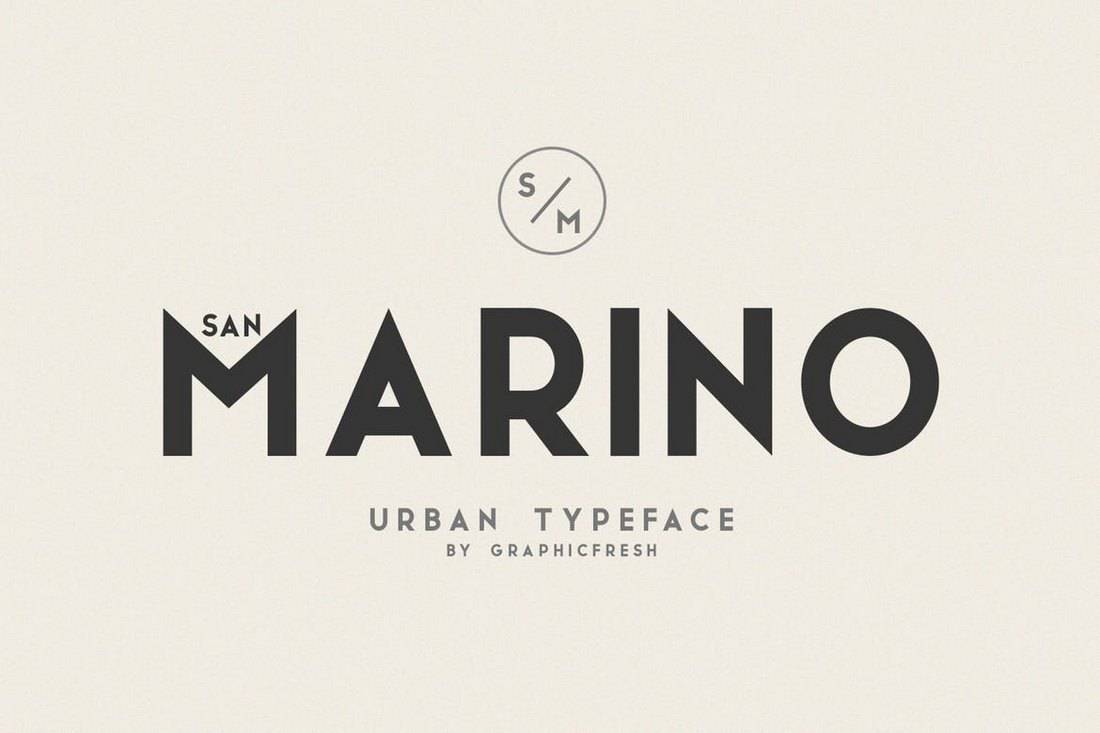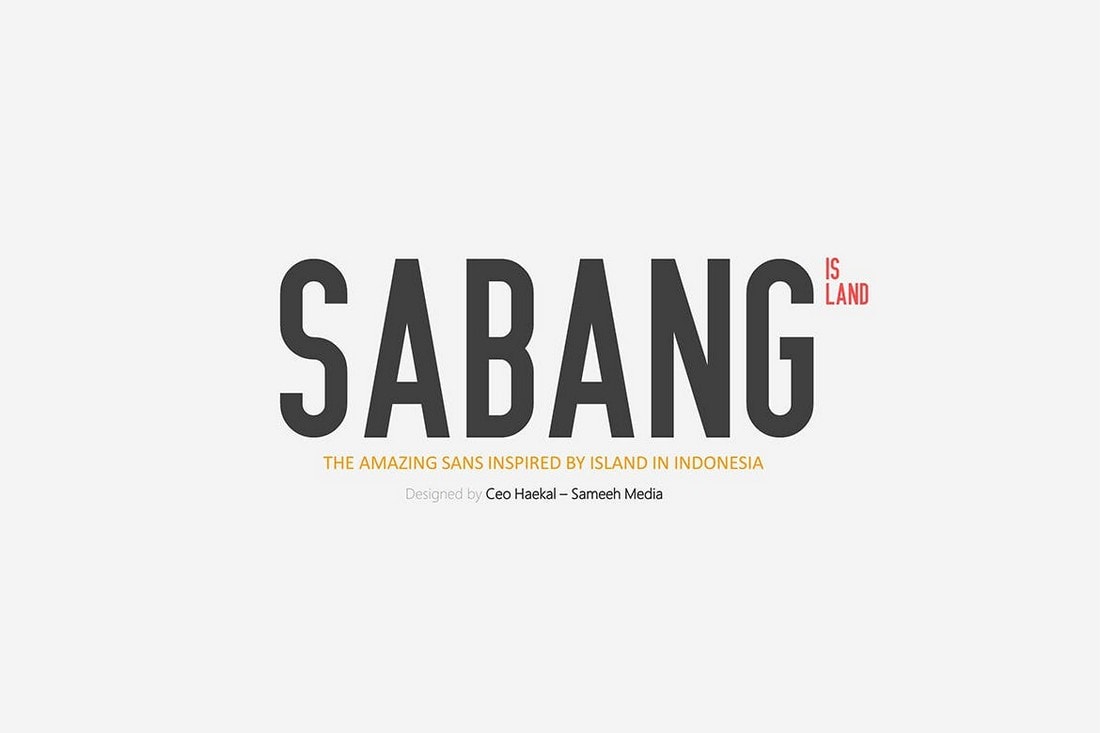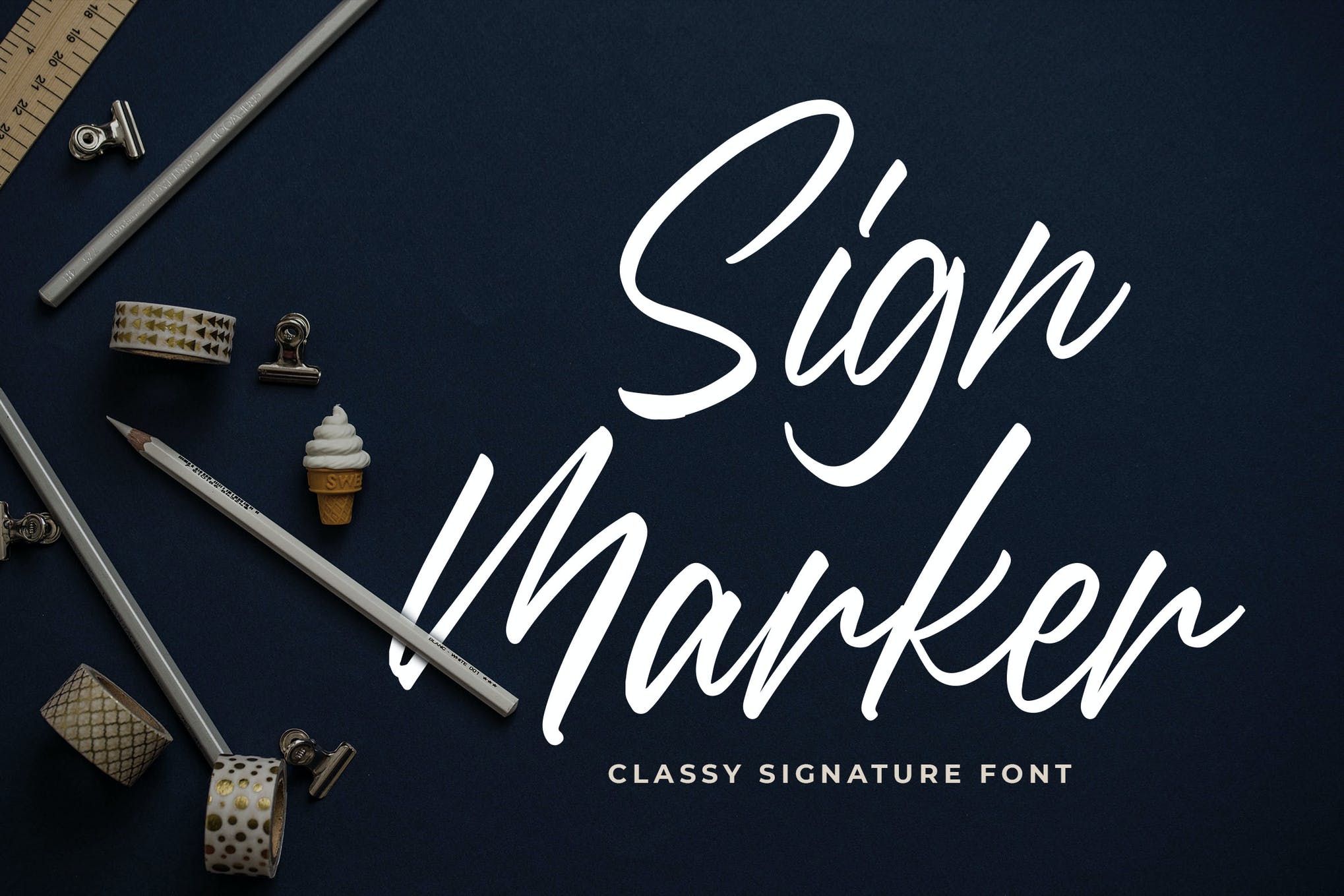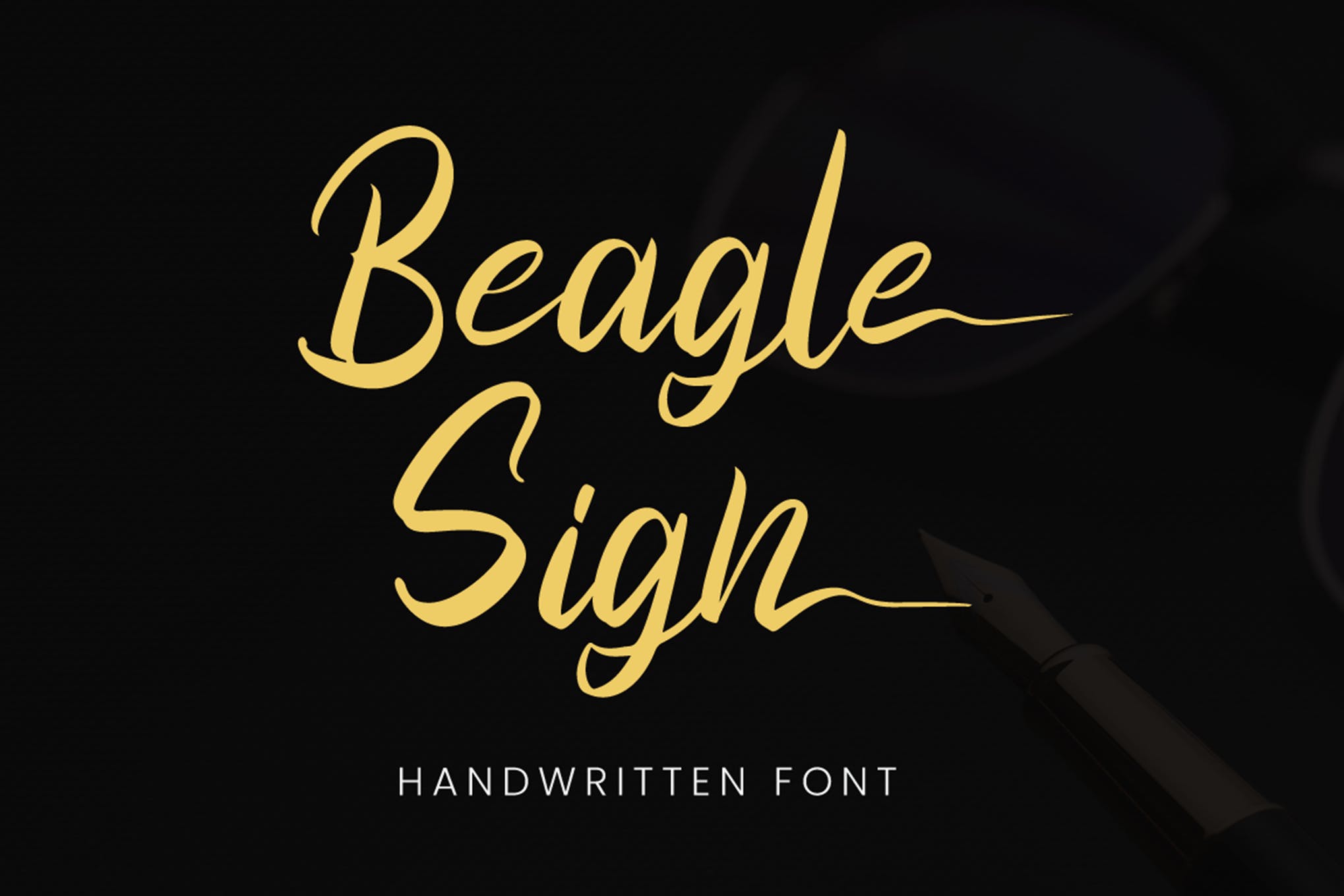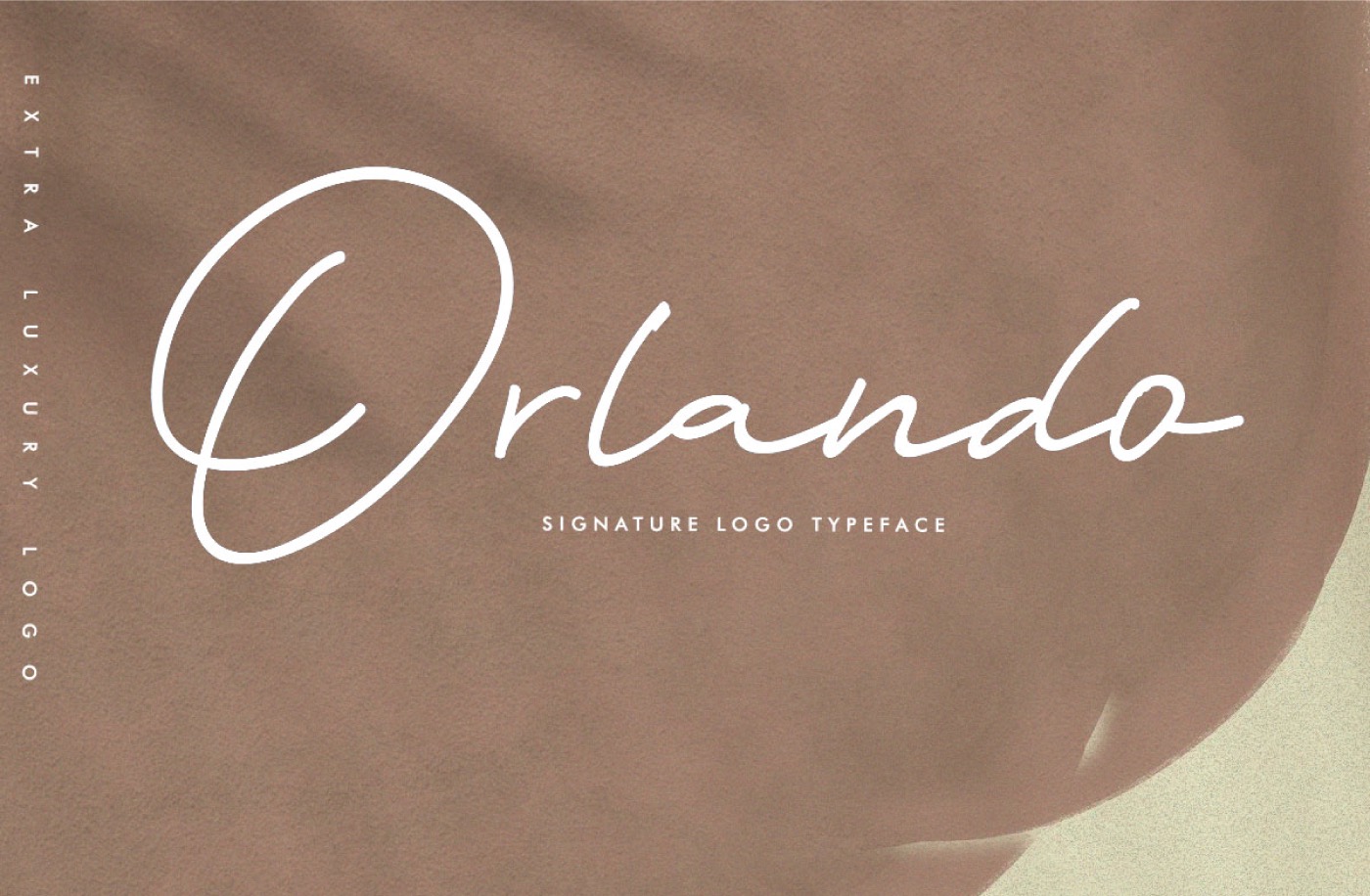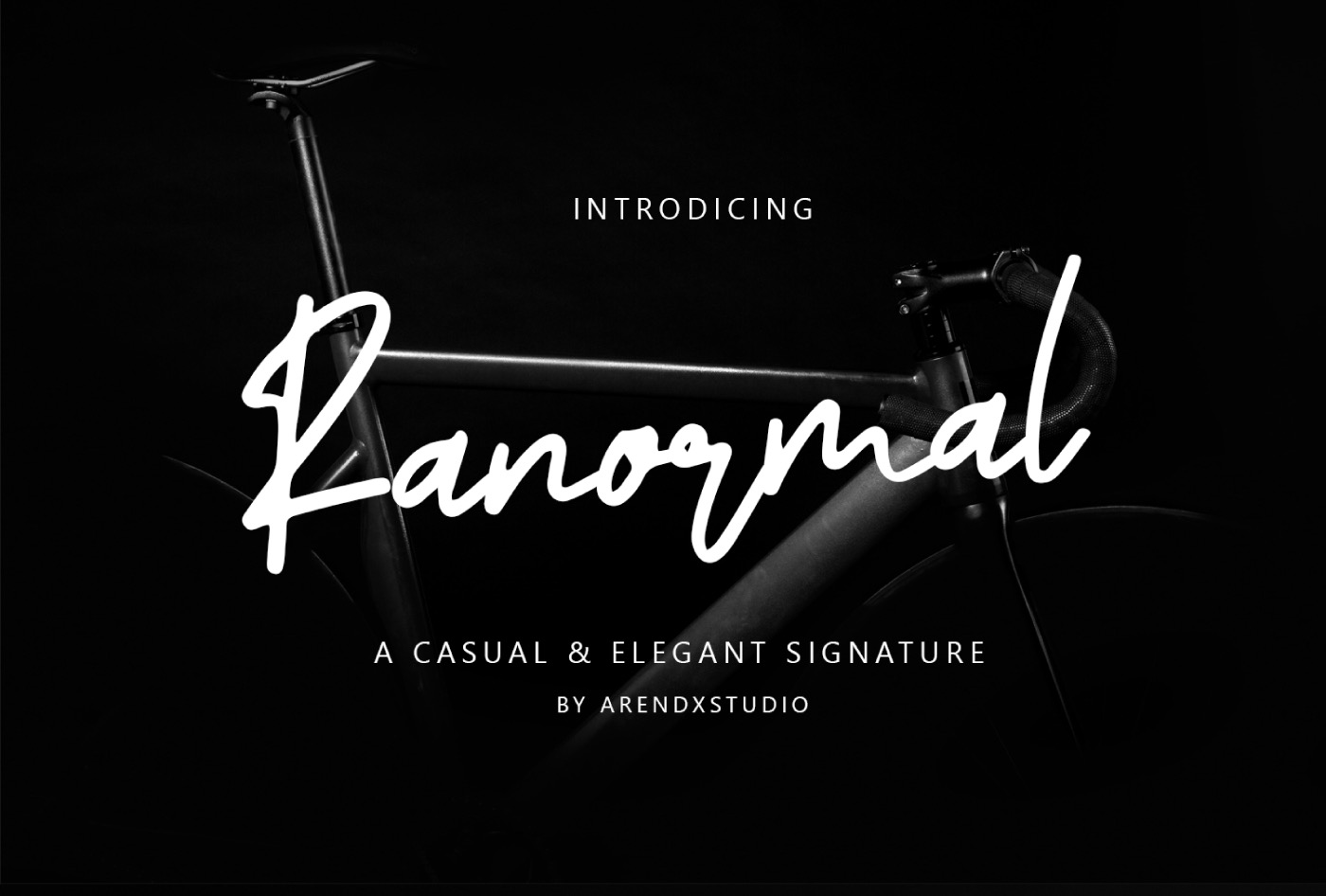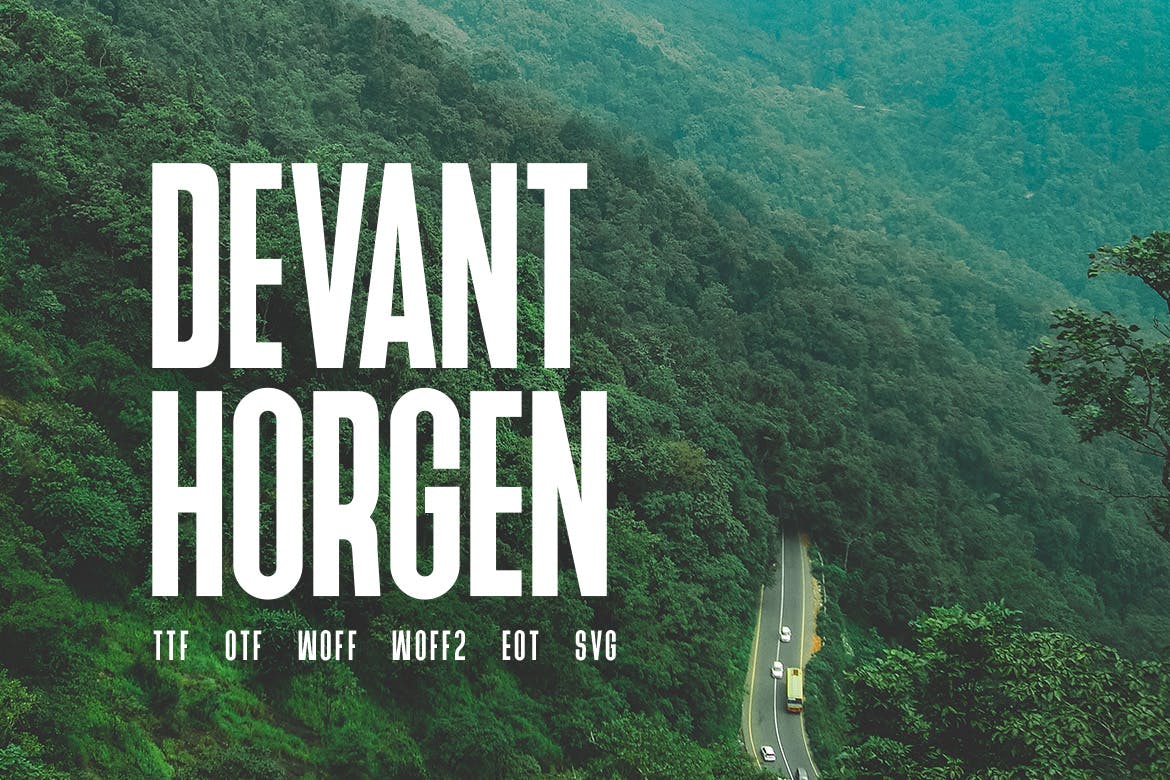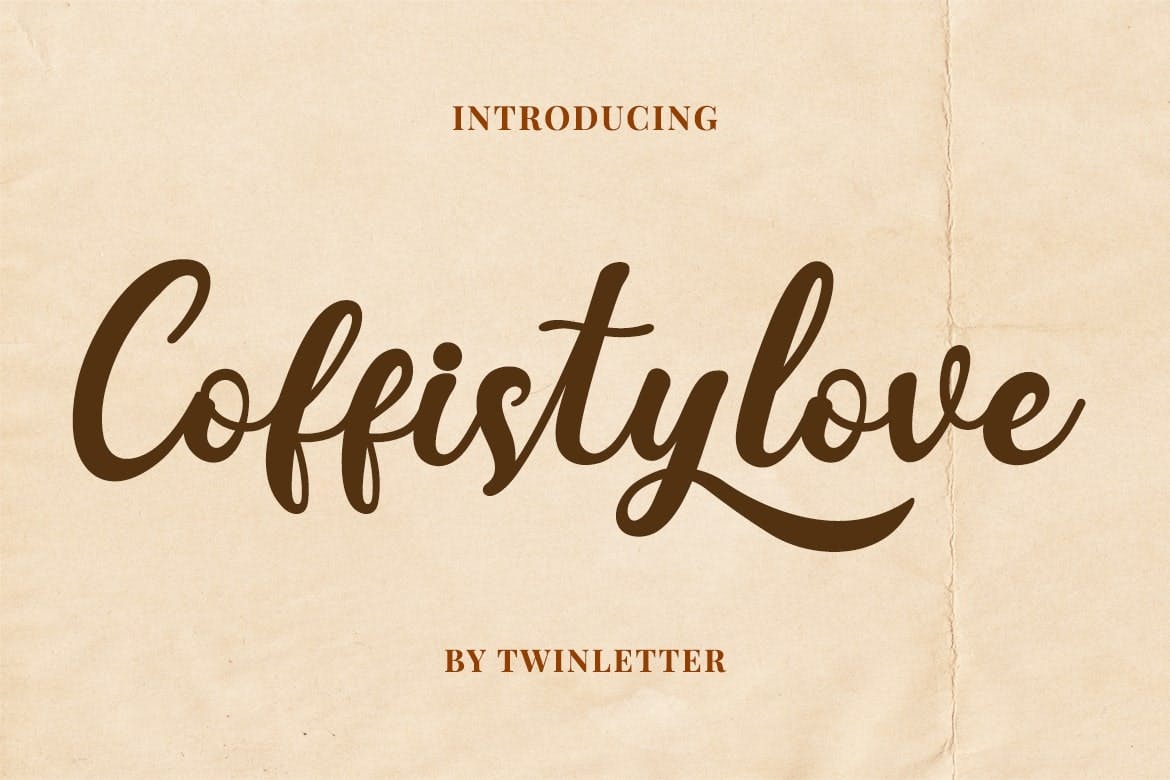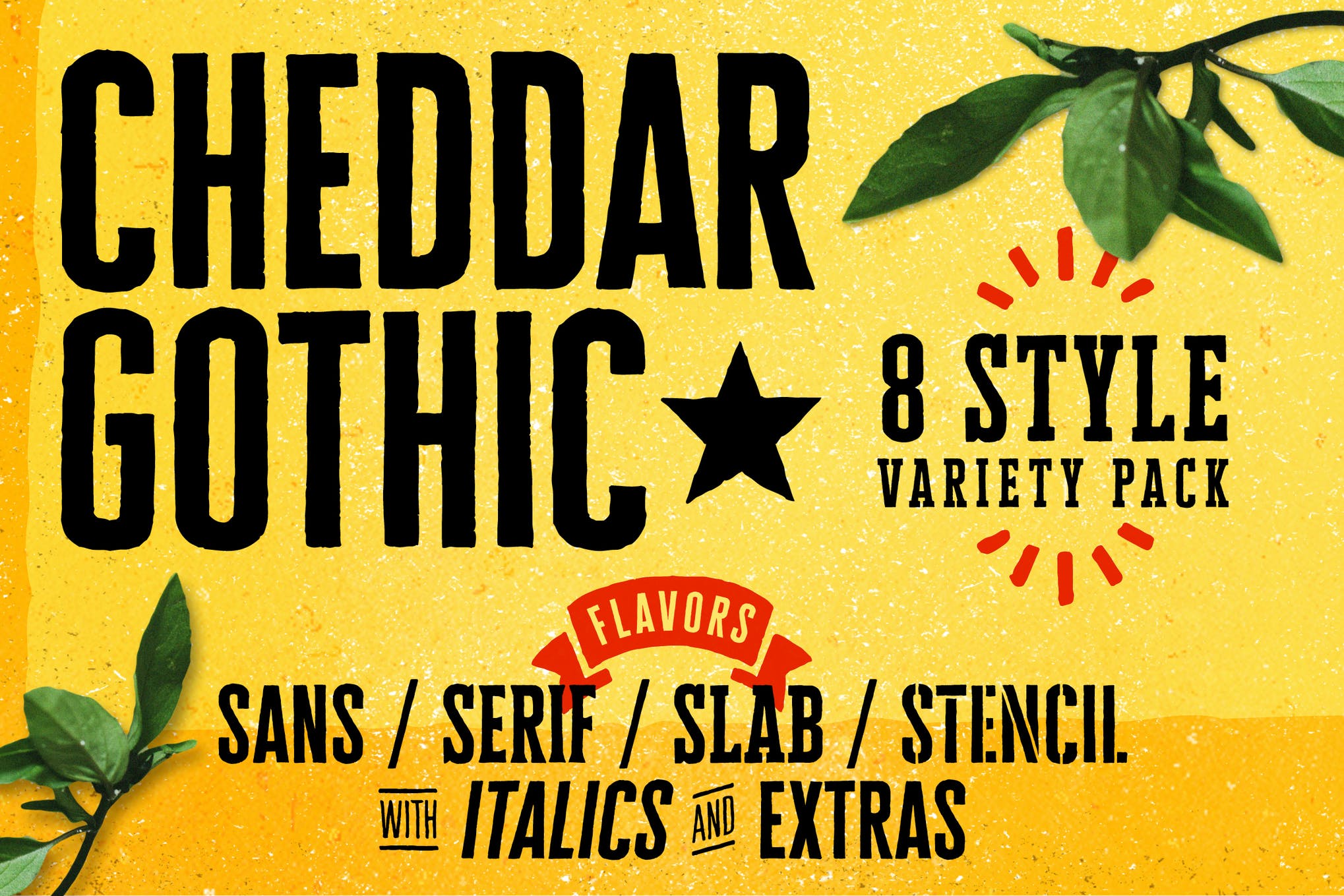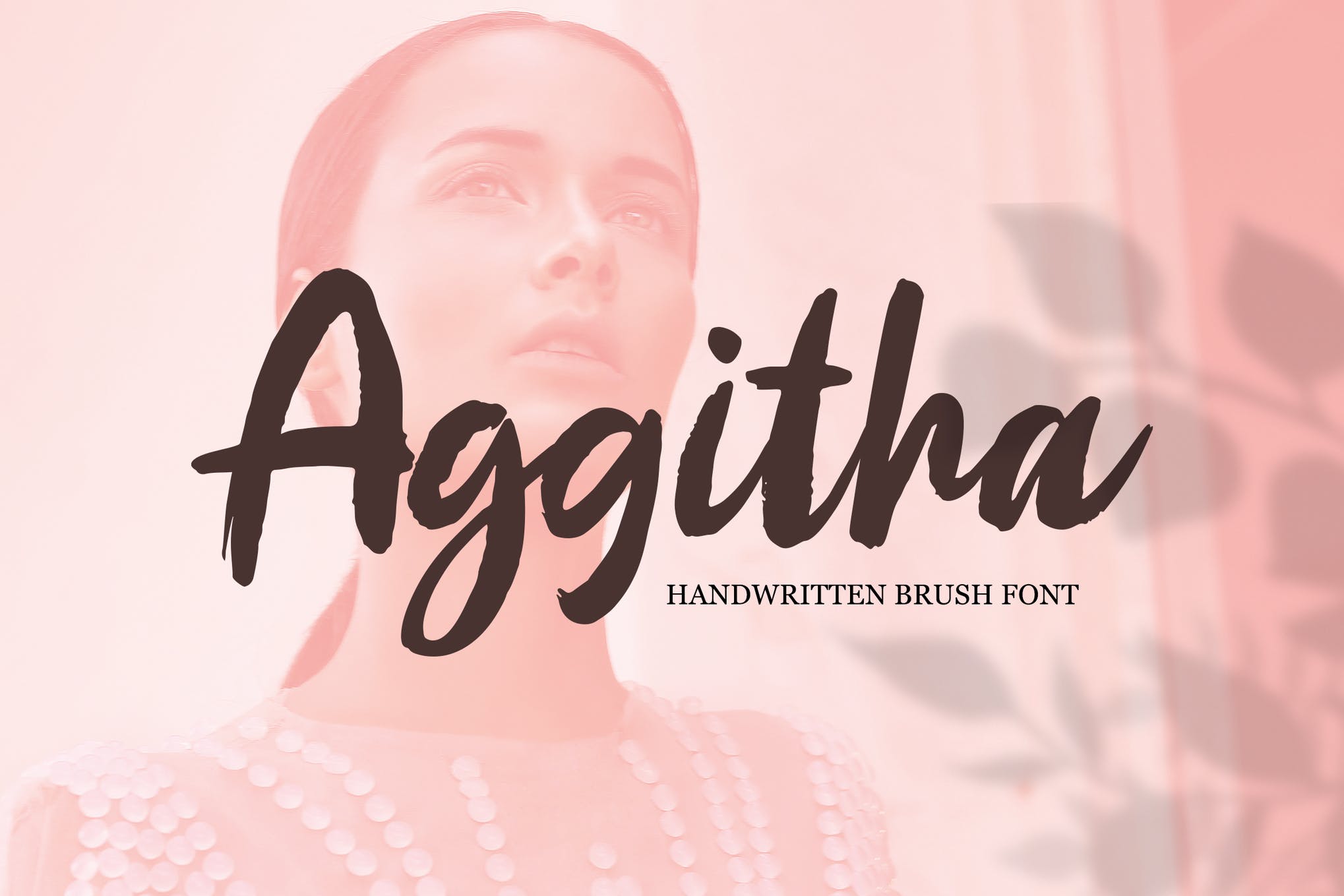
35+ Beste Fonts für Schilder
Ob Sie an einem Schild-Design für ein Café oder eine Luxusboutique arbeiten, die Auswahl der richtigen Schriftart für Ihr Schild trägt wesentlich dazu bei, dass Ihre Beschilderung professioneller und einzigartiger aussieht.
Beim Entwerfen verschiedener Arten von Schildern müssen Sie oft mit spezifischen Standards und Schriftlayouts arbeiten. Aber das bedeutet nicht, dass Sie nicht kreativ werden und einzigartige Schriftarten in Ihren Designs verwenden können.
Eine großartige Schriftart zu finden bedeutet normalerweise, stundenlang im Web zu suchen und enttäuschende Ergebnisse zu erhalten. Um Ihnen Zeit zu sparen und schneller eine kreative und stilvolle Schriftart zu finden, haben wir die besten Schriftarten für Schilder (für alle Arten von Unternehmen und Geschäften) ausgewählt, sowie ein paar hilfreiche Tipps für das Design von Schildern!
Top Pick
San Marino - Urban Font Family
Das Gestalten trendiger Beschilderungen für urbane Geschäfte und Läden wird so viel einfacher, wenn Sie diese Schriftart in Ihrem Repertoire haben. Sie verfügt über ein trendiges und sauberes Design, das für alle Arten von Marken von kleinen Unternehmen bis hin zu Luxusgeschäften geeignet ist.
Die Schriftart kommt in 4 verschiedenen Schriftstilen, einschließlich Regular, Outline, Italic und Sans Serif. Sie ist auch eine Schriftart mit Großbuchstaben.
Warum dies ein Top-Pick ist
Der klassisch saubere Look dieser Schriftart ist das, was sie herausstechen lässt. Die Schriftart eignet sich perfekt für das Gestalten von Titeln für Schilder, die Professionalität zeigen. Die mehrsprachige Unterstützung ist ebenfalls ein zusätzliches Plus.
Sabang Island - Narrow Font For Signs
Sabang ist das perfekte Beispiel für eine saubere und schmale Titelschriftart. Ihr hoher Buchstabendesign macht sie zu einer hervorragenden Wahl für die Gestaltung von Beschilderungen aller Art. Sie kommt auch in zwei Stilen mit sauberem und rauem Design. Die Schriftart enthält sowohl Groß- als auch Kleinbuchstaben.
Fonseca - Art Deco Font Family
Auf den ersten Blick können Sie sehen, dass dies eine großartige Schriftart für die Gestaltung von Schildern für Luxusmarken und High-End-Unternehmen ist. Die Schriftart zeichnet sich durch ein modernes Design aus, das von den Art-Déco-Stilen des 20. Jahrhunderts inspiriert ist. Sie kommt in 8 verschiedenen Schriftgewichten mit Alternativ
– und Kursivschnitten.
Schauen Sie sich Ambattur an, eine moderne Signatur-Schriftart im Kalligrafie-Stil, die auf Visitenkarten, Plakaten, Einladungen und anderen Markenmaterialien atemberaubend aussieht. Sie kommt mit Tonnen von Glyphen, Alternativzeichen und Ligaturen und vielem mehr.
Als nächstes haben wir Sign Marker, eine Pinselstift-Signatur-Schriftart, die Sie schwer davon abhalten können, sie nicht zu berücksichtigen. Sie wird mit einem vollständigen Satz von Groß- und Kleinbuchstaben, Zahlen, Satzzeichen und mehrsprachiger Unterstützung geliefert.
Wenn Sie eine Beschriftungsschrift suchen, die wirklich auffällt, wagen Sie einen Sprung des Glaubens in Beagle Sign, eine stilvolle und einzigartige Schriftart, die sich vielfach auszahlen wird. Probieren Sie sie für Ihr nächstes Markenprojekt aus!
Möchten Sie Ihre Hände auf eine luxuriös aussehende Beschriftungsschrift legen, ohne einen Cent ausgeben zu müssen? Dann schauen Sie sich Orlando an, eine Skript-Schriftart mit großen dramatischen Großbuchstaben und einer breiten Palette von Alternativen und Ligaturen, um Ihre Arbeit ganz nach Ihren Wünschen anzupassen.
Perfekt für eine Vielzahl von Designprojekten ist Ranormal eine atemberaubende Schriftwahl, die als kostenloser Download für den persönlichen und kommerziellen Gebrauch erhältlich ist. Sie ist eine der besten Schriftarten für Schilder, also beeilen Sie sich; greifen Sie jetzt zu!
Bant Achillers - Vintage Singage Font
Wenn Sie an einem Beschriftungsdesign für eine zwanglose oder hippe Marke arbeiten, ist diese Schriftart perfekt für Sie. Sie zeichnet sich durch ein modern-vintage Design aus, das eine Monolinienlayout bietet. Sie enthält sowohl Groß- als auch Kleinbuchstaben sowie Glyphen, um einzigartige Beschilderungen aller Art zu gestalten.
Makuton - Japanese-Style Vintage Font
Dies ist eine einzigartige Schriftart mit einem Design, das von der japanischen Kultur inspiriert ist. Sie enthält ein handgemachtes Schriftbild, das gut zu zwanglosen und modernen Beschilderungen passt. Sie eignet sich am besten für Designs im Zusammenhang mit kreativen Marken und Agenturen.
Manufaktur - Bold Fonts for Signs
Manufaktur ist eine fette Schriftart, die in 5 verschiedenen Schriftgewichten, 3 Schriftstilen und 3 Breiten erhältlich ist. Sie verfügt über ein Design, das von der schwedischen Industriemaschine inspiriert ist. Die Schriftart eignet sich perfekt für die Gestaltung von Beschilderungen im Zusammenhang mit Unternehmensgeschäften und Industrien sowie modernen Marken.